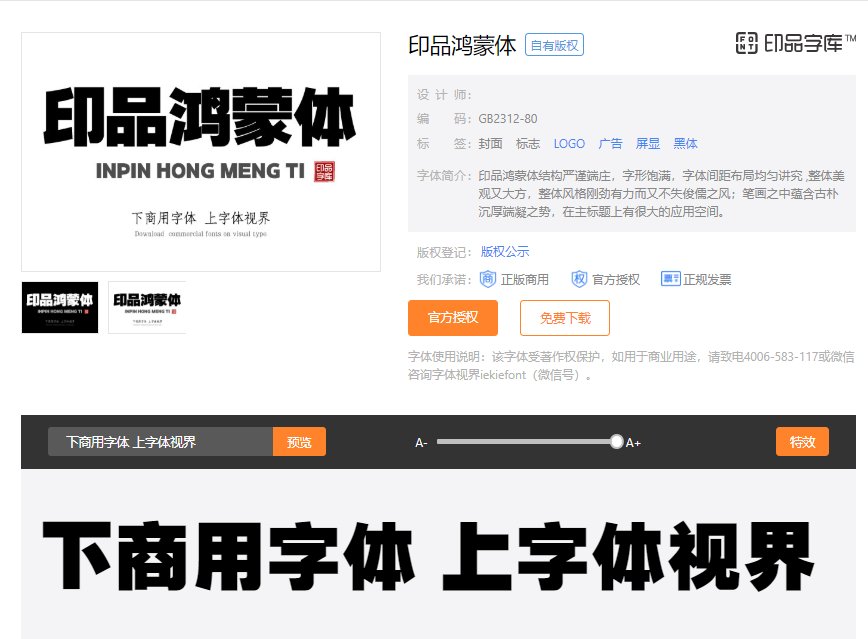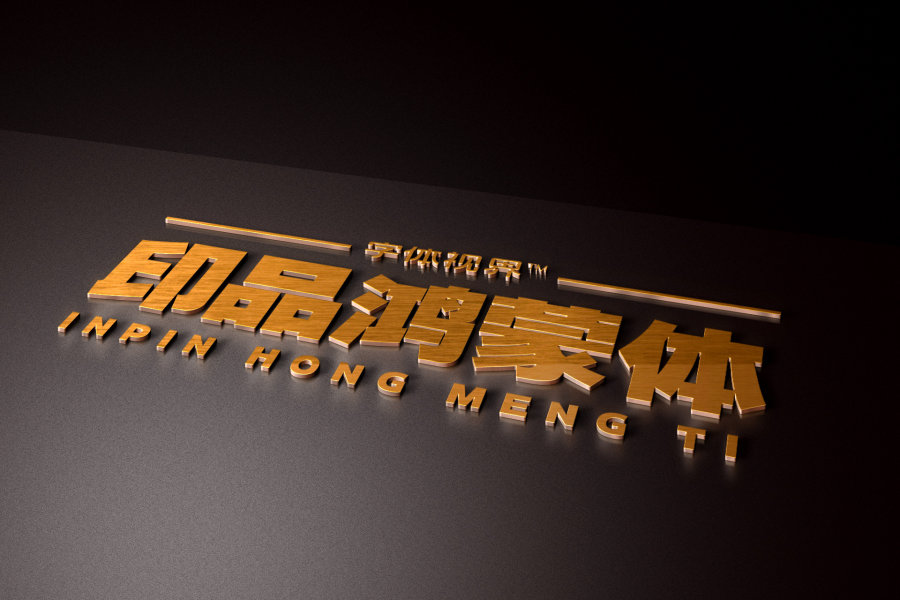
印品鸿蒙体结构严谨端庄,字形饱满,字体间距布局均匀讲究 ,
整体美观又大方;
横竖笔画粗细保持一致超粗黑,整齐划一,凸显出精简精干的特点,
粗壮有力的笔划赋予其力量感,整体风格刚劲有力而又不失俊儒之风;
笔画之中蕴含古朴沉厚端凝之势,在主标题上有很大的应用空间。笔画粗壮,适合与宋体混排,
夹在正文中间用来排重点句、重点词组效果很好,是一款超粗黑字体。